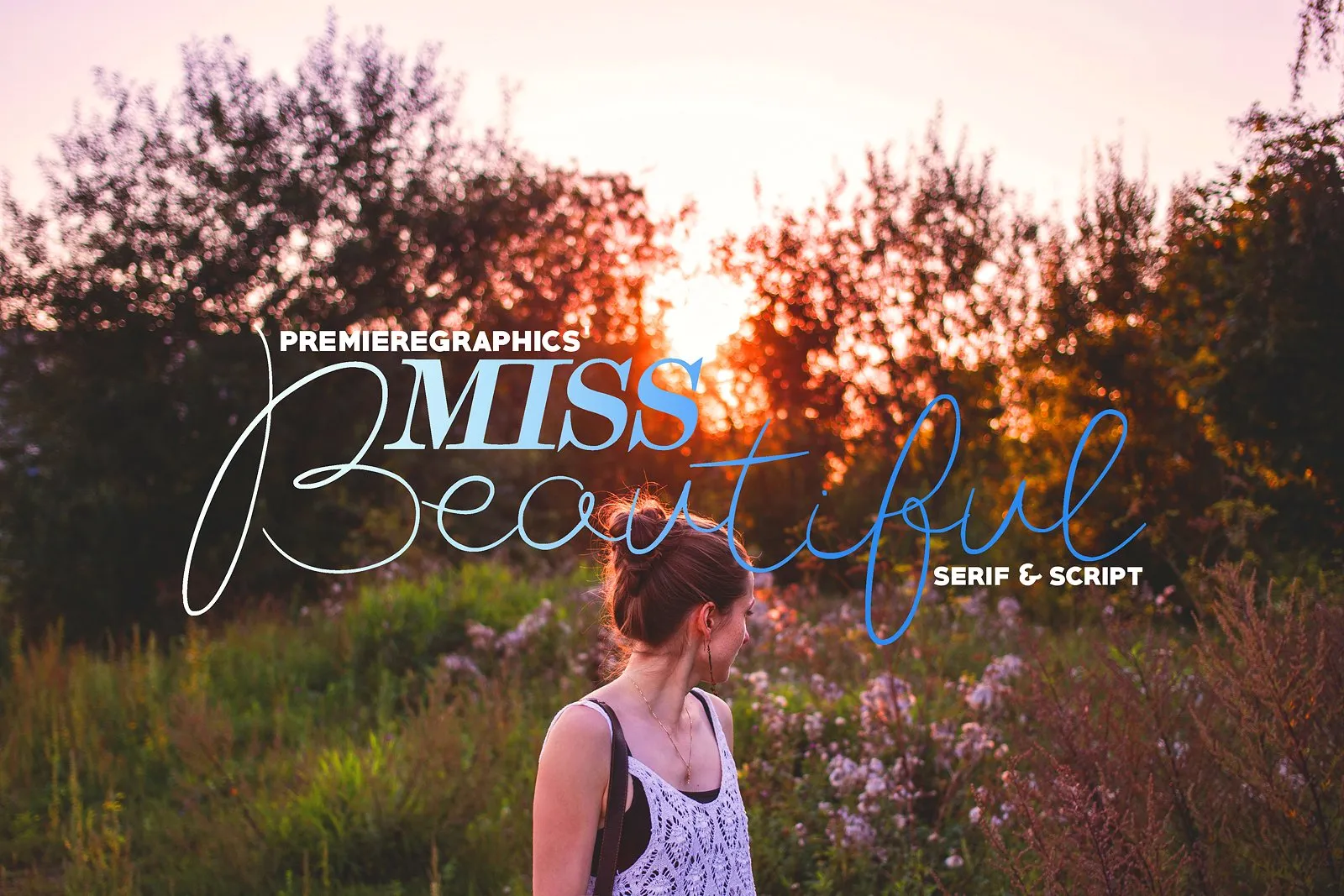
Miss Beautiful Script Font – Download Grátis
A Miss Beautiful Script Font é uma seleção perfeita para designers buscando trazer uma personalidade única aos seus projetos digitais. As três linhas distintas e dois swashes disponíveis garantem um amplo leque de combinações, tornando-a uma opção ideal não apenas para cartões de casamento ou banners, mas também para blogs, fotos e designs que valorizam a escrita a mão. Introduzida pela Premiere Graphics, essa fonte é perfeitamente adaptada à tipografia do século XXI e ao movimento cada vez mais popular de design hand-made. Com sua rica história na arte da escrita, a Miss Beautiful oferece um toque único para qualquer projeto visual que você esteja trabalhando. Seja para criar um layout elegante em blogs pessoais ou uma identidade forte para uma marca, essa fonte é perfeita. E, por ser projetada para designers, ela traz um toque de personalidade e originalidade a cada projeto, garantindo sempre um resultado profissional. Para quem está procurando pela perfeição no design gráfico, a Miss Beautiful Script Font é a escolha certa. Além disso, sua versatilidade faz dela uma fonte indispensável para designers e aspirantes à carreira na área de design gráfico.